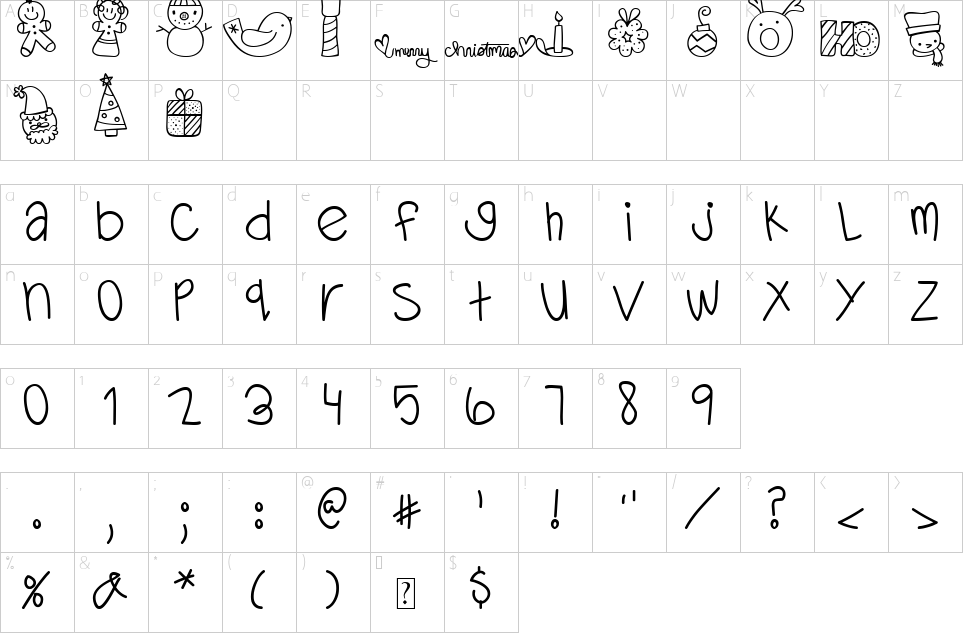
Descubra a MTF Dear Santa font, uma fonte que combina uma personalidade encantadora com um toque de criatividade. Lançada pelo designer de fontes Miss Tiina Fonts, essa fonte é ideal para aqueles que querem adicionar um toque especial a seus designs, especialmente nesse período especial do ano. Com um design único e um estilo que remete diretamente à essência de Natal, a MTF Dear Santa font é perfeita para cartões de Natal, ilustrações, decoração de festas, e qualquer projeto gráfico que desejem transmitir alegria e harmonia. Esta fonte foi descarregada 59,153 vezes e continua a ser adorada por designers de todo o mundo por sua simplicidade e personalidade única. Descubra por que a MTF Dear Santa font é uma escolha inteligente para qualquer projeto gráfico que deseja uma pitada de encanto e amabilidade.